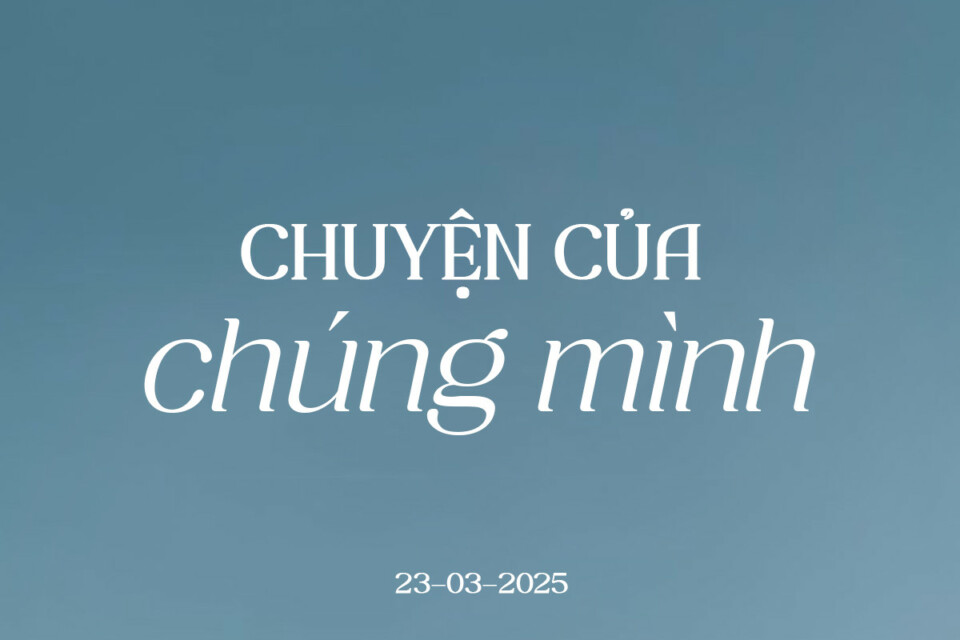
Font việt hoá MJ Kedanty ( 2 style) – Bộ font chữ thanh lịch cho thiết kế sáng tạo
Trong thế giới thiết kế đồ họa hiện đại, việc tìm kiếm một bộ Font Chữ vừa mang nét cổ điển vừa giữ được sự tinh tế là điều không hề dễ dàng. Font việt hoá MJ Kedanty ( 2 style) chính là giải pháp hoàn hảo dành cho những ai yêu thích phong cách Serif sang trọng. Với khả năng hỗ trợ tiếng Việt trọn vẹn, bộ font này đã xóa bỏ rào cản về lỗi hiển thị dấu, giúp người dùng tự tin hơn trong quá trình sáng tạo nội dung văn bản hay các ấn phẩm truyền thông chuyên nghiệp.
Đặc điểm nổi bật của Font việt hoá MJ Kedanty ( 2 style)
Phong cách thiết kế đa dạng
Bộ Font việt hoá MJ Kedanty ( 2 style) bao gồm hai biến thể chính là Regular và Italic. Bản Regular mang đến sự vững chãi, rõ nét với các đường nét Serif mảnh mai nhưng sắc sảo. Trong khi đó, bản Italic lại tạo cảm giác mềm mại, bay bổng, rất phù hợp để nhấn mạnh các đoạn trích dẫn hoặc tiêu đề phụ. Sự kết hợp giữa hai phong cách này giúp nhà thiết kế dễ dàng tạo ra sự tương phản thị giác cần thiết mà không cần phải tìm kiếm thêm các bộ font phụ trợ khác.
Tính ứng dụng cao trong học tập và công việc
Nhờ vào tính thẩm mỹ cao, font chữ này thường được ứng dụng rộng rãi trong thiết kế bìa sách, thiệp mời, logo thương hiệu hoặc các slide thuyết trình trong môi trường sư phạm. Đặc biệt, đối với các bạn học sinh và sinh viên, việc sử dụng một bộ font thanh lịch như MJ Kedanty sẽ giúp bài làm trở nên ấn tượng và chuyên nghiệp hơn trong mắt thầy cô.
Kết luận về bộ font MJ Kedanty